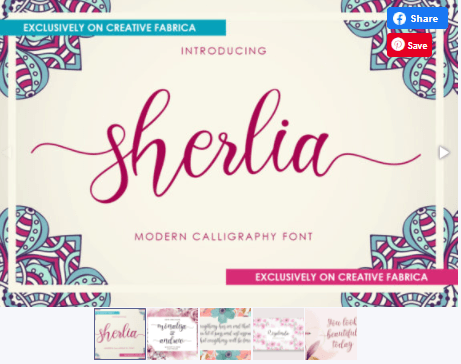
Sherlia Script Font
Sherlia Script - тонкий и элегантный рукописный шрифт. Его четкие и хорошо сбалансированные буквы делают этот шрифт шедевром. Этот шрифт закодирован в кодировке PUA, что означает, что вы можете легко получить доступ ко всем глифам и штрихам!